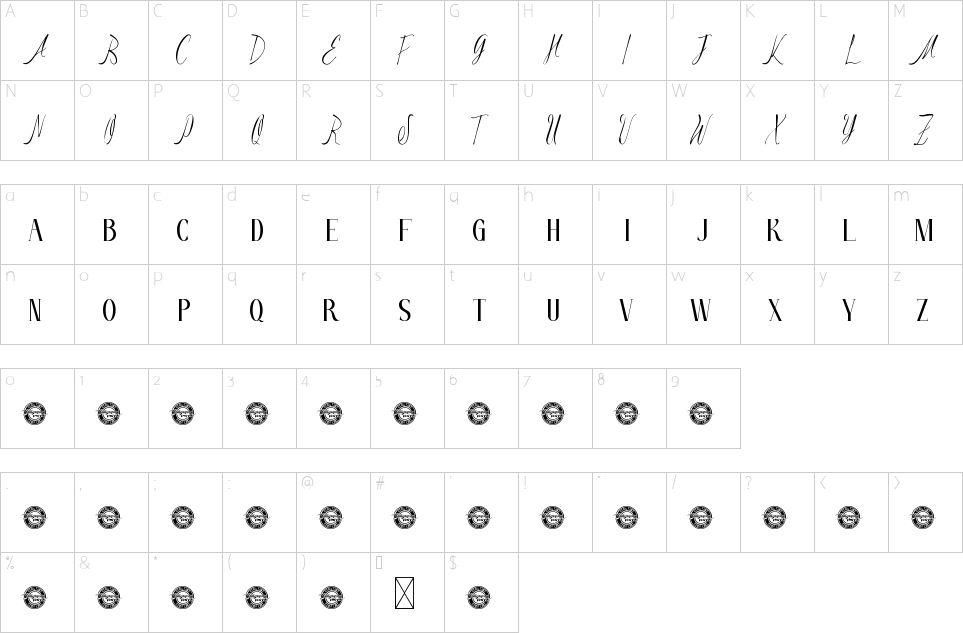
A fonte Maisa Yasmine é uma obra de arte que surgiu dos lábios de um designer de calligrafia, chamado CalligraphyFont. Suavemente curva e elegante, Maisa Yasmine é perfeita para aqueles que buscam uma fonte gráfica que se adapta perfeitamente tanto aos projetos digitais quanto aos impressos. Desenvolvida para oferecer uma variedade de opções, essa fonte é ideal para designers de gráficos, estilistas de marca e criadores de sites que procuram uma fonte que se destaca e se adapta aos seus projetos. Ela foi projetada para ser utilizada tanto na sua versão Windows quanto na Mac, oferecendo uma gama de opções para quem deseja dar um toque único a suas criações. Como uma fonte gratuita de 1001 Free Fonts, Maisa Yasmine é uma fonte que traz uma paleta de nuances à sua arte digital.